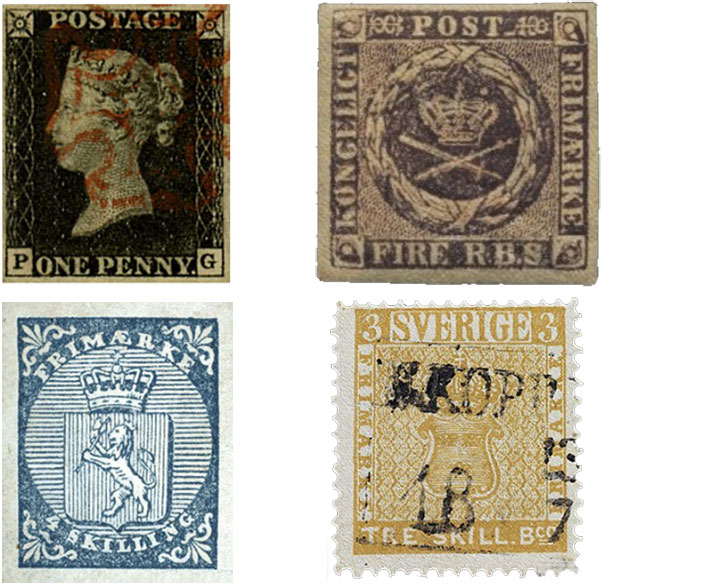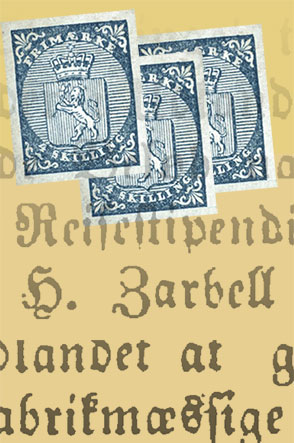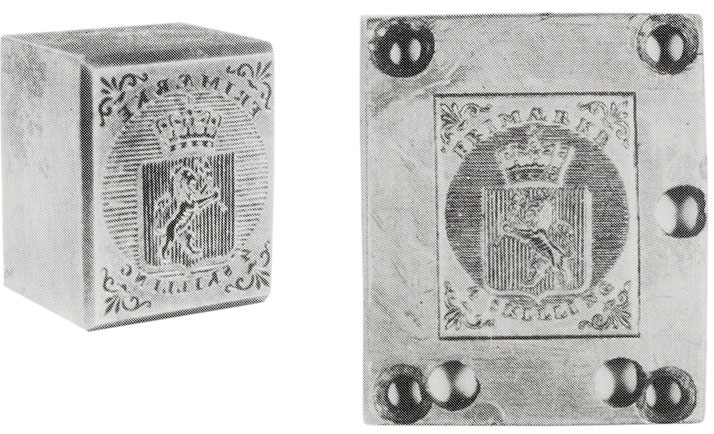
Det har vært en svært svak tradisjon for skriftstøping i Norge. Blytypene er i all hovedsak blitt importert fra utlandet, og det første lille skriftstøperiet på norsk jord ble etablert først på 1860-tallet. Men mekanikus N. A. H. Zarbell i Christiania hadde lært skriftstøpingskunsten et tiår tidligere, og teknikken kunne anvendes også til andre formål – blant annet til å framstille trykkoriginalene (klisjeene) til frimerker. Zarbell fikk i 1854 oppdraget med å produsere det første norske frimerket. Det innebar også gravering av bokstaver og tall.
Litteraturen om det første norske frimerket er betydelig. Filatelister, nasjonalt og internasjonalt, har interessert seg for dets spesielle historie – og for dets variasjoner av små feil.1 «A marvellous postage stamp», heter det i en publikasjon om frimerket.2
Det første norske frimerket ble tatt i bruk i 1855. Her er det rentegnet i Tore Gjelsviks bok Norway Number One, 1994.
Denne artikkelen begynner med produsenten Niels Andreas Harboe Zarbell og hans liv og virksomhet, før jeg trekker fram noen tekniske problemstillinger knyttet til produksjonen av frimerket. En typografisk vurdering av skriften han skar, i form av tegnene i ordene FRIMÆRKE og 4 SKILLING, avslutter artikkelen.
Min interesse for Zarbell og det første norske frimerket startet med følgende melding i flere aviser i 1852:
– Efter Departementet for det Indres Indstilling er ved kongelig Resolution af 7de October sidstleden bestemt:
«At der af det af Storthinget til Understøttelse for duelige Haandverkere, der i Udlandet ville uddanne sig i deres Fag, bevilgede Beløp naadigst tilstaaes efternævnte Haandverkere Reisestipendier, nemlig:
1) Mechanikus N. A. H. Zarbell af Christiania 200 Spd., for i Udlandet at gjøre sig nøiere bekjent med det Fabrikmæssige ved Skriftstøberier;
Christiania-Posten 10.11.1852.
En norsk skriftstøper, som så et marked for norsk-støpte skrifter til de norske boktrykkeriene! Dette tror jeg ingen tidligere har undersøkt. Hvem var han, hvor reiste han med stipendpengene, hva førte denne kunnskapen til seinere? Dette var noen av mine spørsmål.
Mechanikus Zarbell
Niels Andreas Harboe Zarbell (1805–1856) ble født i Berstad i Hurum prestegjeld. Han tok examen artium og begynte i 1828 studier ved Universitetet i Christiania. Zarbell betegnet seg da som Studiosus Theol.3 Men studiene måtte oppgis på grunn av problemer med øynene.4
Zarbell interesserte seg for matematikk og for mekanisk produksjon, og startet i 1838 det som i historien om den norske mekaniske industrien er omtalt som Norges første mekaniske verksted, i hvert fall det der det også ble bygget maskiner. Det lå først i Tomtegaten på Vaterland, men flyttet i 1844 til hans nyinnkjøpte eiendom øst for Slottsparken, ved dagens St. Olavs gate og Pilestredet. Verkstedet skal ha inneholdt smie, fileverksted, dreierverksted og metallstøperi. 17. desember 1844 ble et nybygg på 180 m2 i to etasjer på eiendommen taksert. Her var det ovner, to dreiebenker og to skrustikker, blant mye verktøy.5
Zarbell er blitt betegnet som et mekanisk geni. I åra omkring 1840 var han engasjert av Universitetet som modellsnekker for å reparere og holde ved like dets modellsamling, som bl.a. inkluderte en dampmaskin. Han var blitt anbefalt til jobben av professorene Esmark og Hansteen for sitt «mechaniske Talent og Brugbarhed for Posten».6 Blant produktene fra hans verksted er nevnt en slagpresse og en «knaldhættemaskin». Han ble brukt som en autoritet på å vurdere kapasiteten på en ny brannsprøyte, og var med på å teste effektiviteten til et brannskap.
Da Den tekniske forening ble startet i Christiania i 1847 ble han valgt til sekretær i styret. Zarbell tok på seg mange oppgaver i denne store og betydningsfulle foreningen, som ble startet på initiativ av professor i kjemi Moritz Christian Julius Thaulow. Formålet var «at befordre den intellektuelle og praktiske Udvikling af Hovedstadens haandværksdrivende Indvaanere».7
Zarbell holdt blant annet foredrag og demonstrasjoner av mekaniske apparater. På det første ordinære møtet i foreningen i august samme år viste han fram «En meget stor Skrue til Slagpræsse, (...) Skruens trelødige Gænger med den for en Slagpresse fornødne Stigning befandtes særdeles nøiagtig skaarne. Pressen eies av Juveleer Tostrup og benyttes til Presning af Sølvarbeide». I november samme år holdt han foredrag om «konstruktionen af de forskjellige Slags Skruer, og over de praktiske Methoder ved disses Forarbeidelse».8
Eksempel på slagpresse. Denne ble brukt i et bokbinderverksted, og tilhører Norsk teknisk museum. Slagpressen som Zarbell hadde bygget ble brukt av juveler Tostrup til å presse produkter av sølv.
Da Haandværkersvendenes Centralforening ble startet i Christiania i 1849 betegnet Zarbell i en tale initiativet (noe patriarkalsk) som en «Hæder for Svendene, at de af egen Drift og uden andres Ledelse have opfattet Ideen om at stifte en saadan Forening ...»9 Foreningen samarbeidet nært med Den tekniske forening, som på sin side var for mestere, borgere og akademikere, og av avisene ser man at praktikeren Zarbell holdt mange foredrag i svenneforeningen.
Dette var en tid for raske tekniske framskritt og økende industrialisering, og mange ville at Norge skulle ta del i denne utviklingen. Offentlige utstillinger av utvalgte produkter var et vanlig tiltak. Den tekniske forening arrangerte sin første utstilling i februar 1848 under markedsdagene i Christiania. Seinere fikk foreningen ansvaret for den norske deltakelsen ved den første verdensutstillingen, i London i 1851.10
Frimerket er vel det aller minste trykte produktet, men har ikke desto mindre en interessant grafisk historie. Ikke minst i Norge, der frimerket over, det første norske, ble tegnet, gravert og støpt til klisjeer av mekanikus Zarbell, og trykt i Det Wulfsbergske Officin. Det ble tatt i bruk i 1855. Zarbell hadde et par år tidligere fått stipend av Stortinget for å lære seg skriftstøperkunsten, noe som gjorde ham i stand til å produsere frimerket.